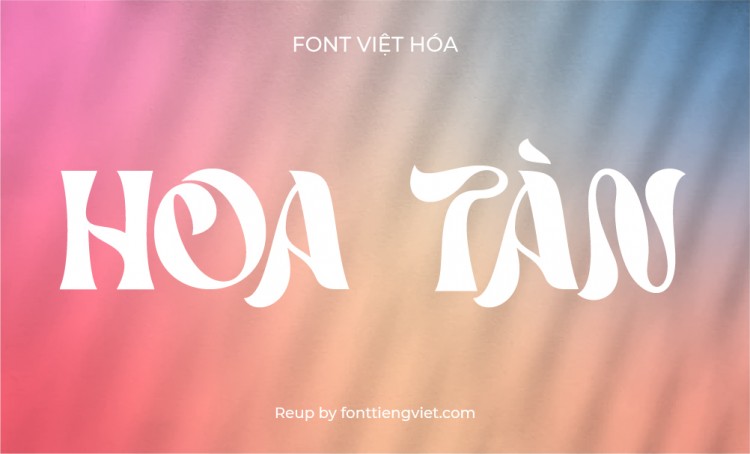
Font việt hóa SVN Lostar
Font việt hóa SVN Lostar – Phông chữ phong cách cổ điển cho thiết kế độc đáo
Giới thiệu về Font việt hóa SVN Lostar trong thiết kế đồ họa
Trong thế giới sáng tạo, việc lựa chọn một Font Miễn Phí chất lượng luôn là ưu tiên hàng đầu của các nhà thiết kế. Font việt hóa SVN Lostar nổi lên như một lựa chọn hoàn hảo nhờ sự kết hợp tinh tế giữa nét chữ cổ điển và hơi thở hiện đại. Đây là bộ font mang phong cách Serif với các đường nét thanh mảnh, uốn lượn mềm mại, giúp tạo nên dấu ấn riêng biệt cho mọi sản phẩm thị giác. Việc sử dụng Font việt hóa SVN Lostar không chỉ giúp thông điệp trở nên rõ ràng mà còn tăng tính thẩm mỹ đáng kể cho bản vẽ.
Những đặc điểm nổi bật của Font việt hóa SVN Lostar
Tính ứng dụng linh hoạt trong nhiều lĩnh vực
Font việt hóa SVN Lostar được đánh giá cao bởi khả năng thích nghi tốt trên nhiều nền tảng khác nhau. Các bạn học sinh và giáo viên có thể ứng dụng bộ font này để làm bài thuyết trình, thiết kế bìa sách hoặc trang trí các bảng tin nhà trường. Đặc biệt, nhờ đã được Việt hóa hoàn chỉnh, người dùng sẽ không gặp phải các lỗi hiển thị dấu câu khó chịu, giúp quy trình làm việc trở nên mượt mà và chuyên nghiệp hơn.
Vẻ đẹp sang trọng và chuyên nghiệp
Mỗi ký tự trong bộ Font việt hóa SVN Lostar đều được chăm chút tỉ mỉ với độ tương phản cao giữa các nét dày và mỏng. Điều này tạo nên cảm giác sang trọng, thường được dùng trong các thiết kế thiệp mời, logo thương hiệu cao cấp hoặc tiêu đề tạp chí. Sự cân bằng trong bố cục chữ giúp người xem dễ dàng tiếp nhận nội dung mà vẫn cảm nhận được sự nghệ thuật trong từng con chữ.
Kết luận và cách sở hữu bộ font chữ ấn tượng